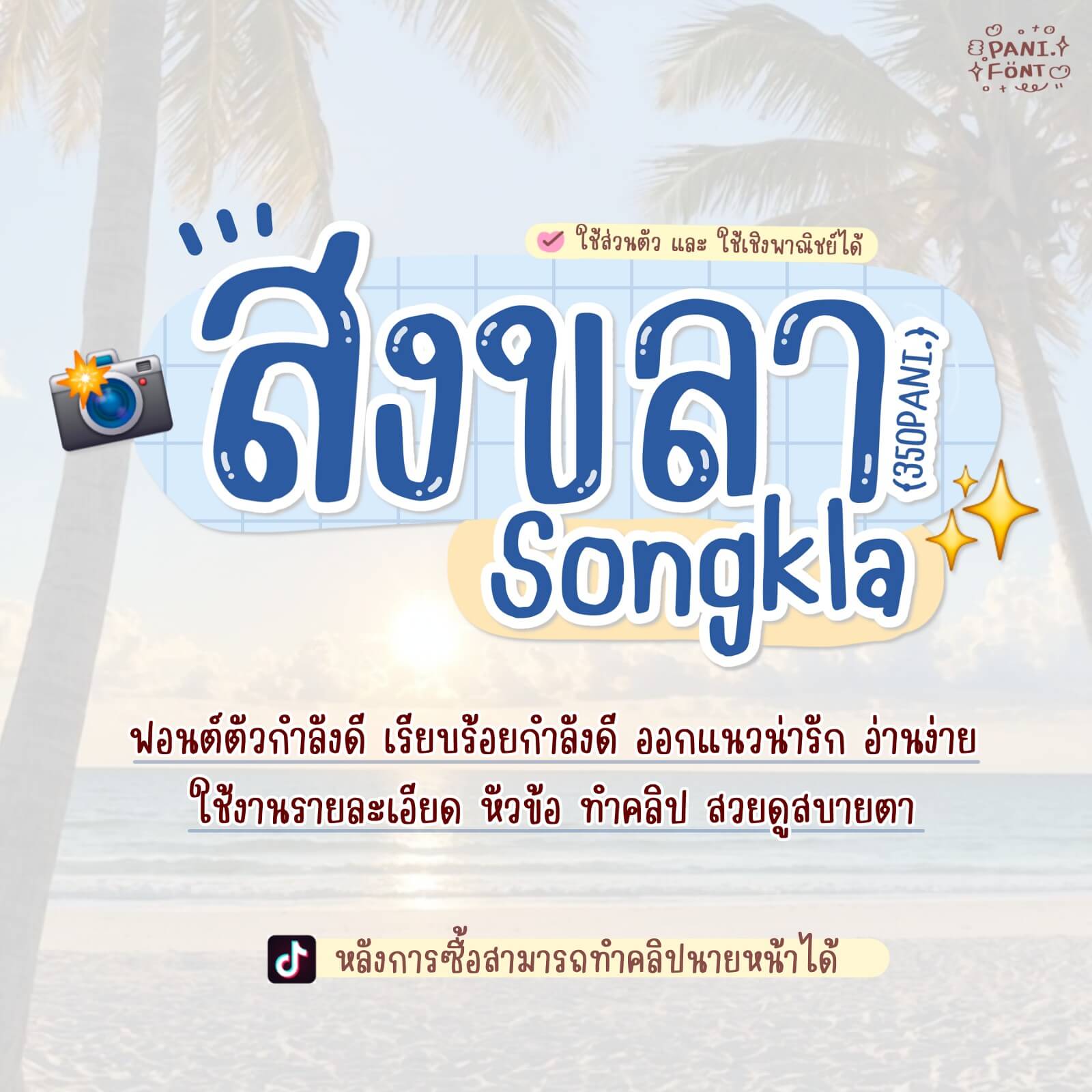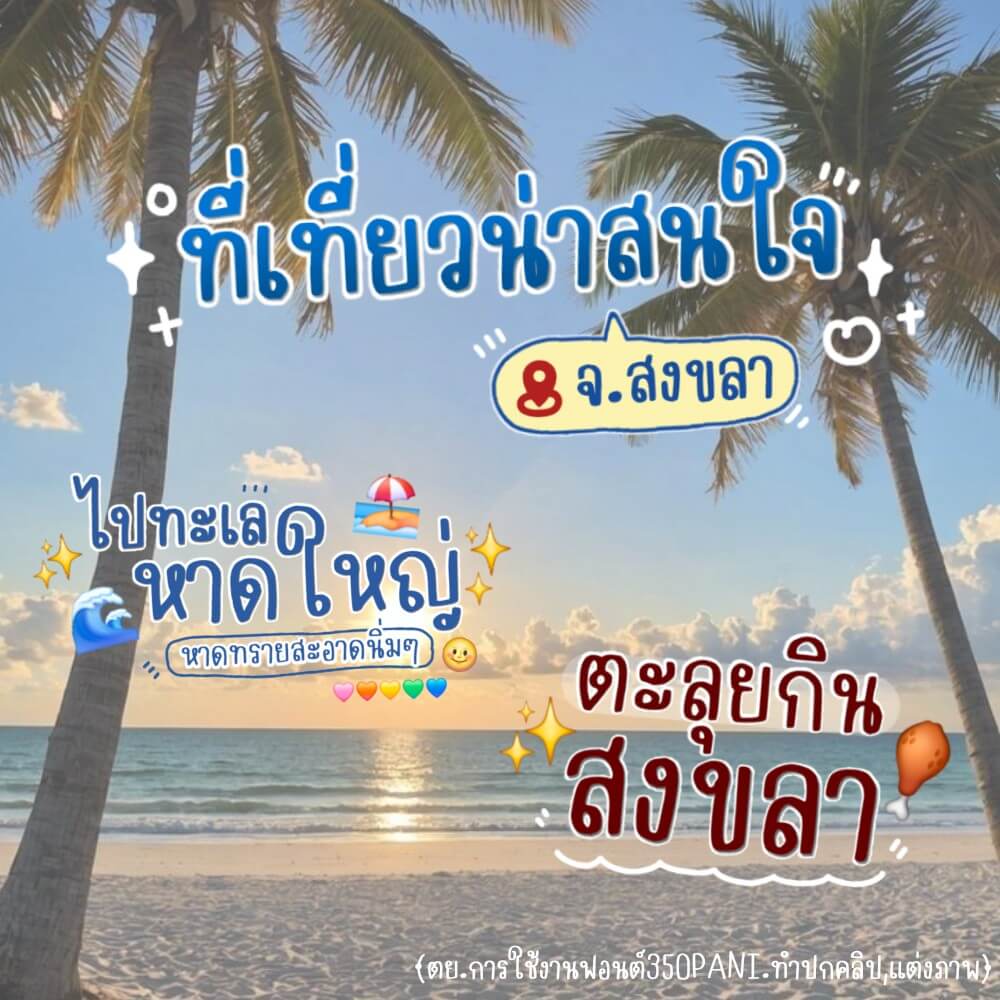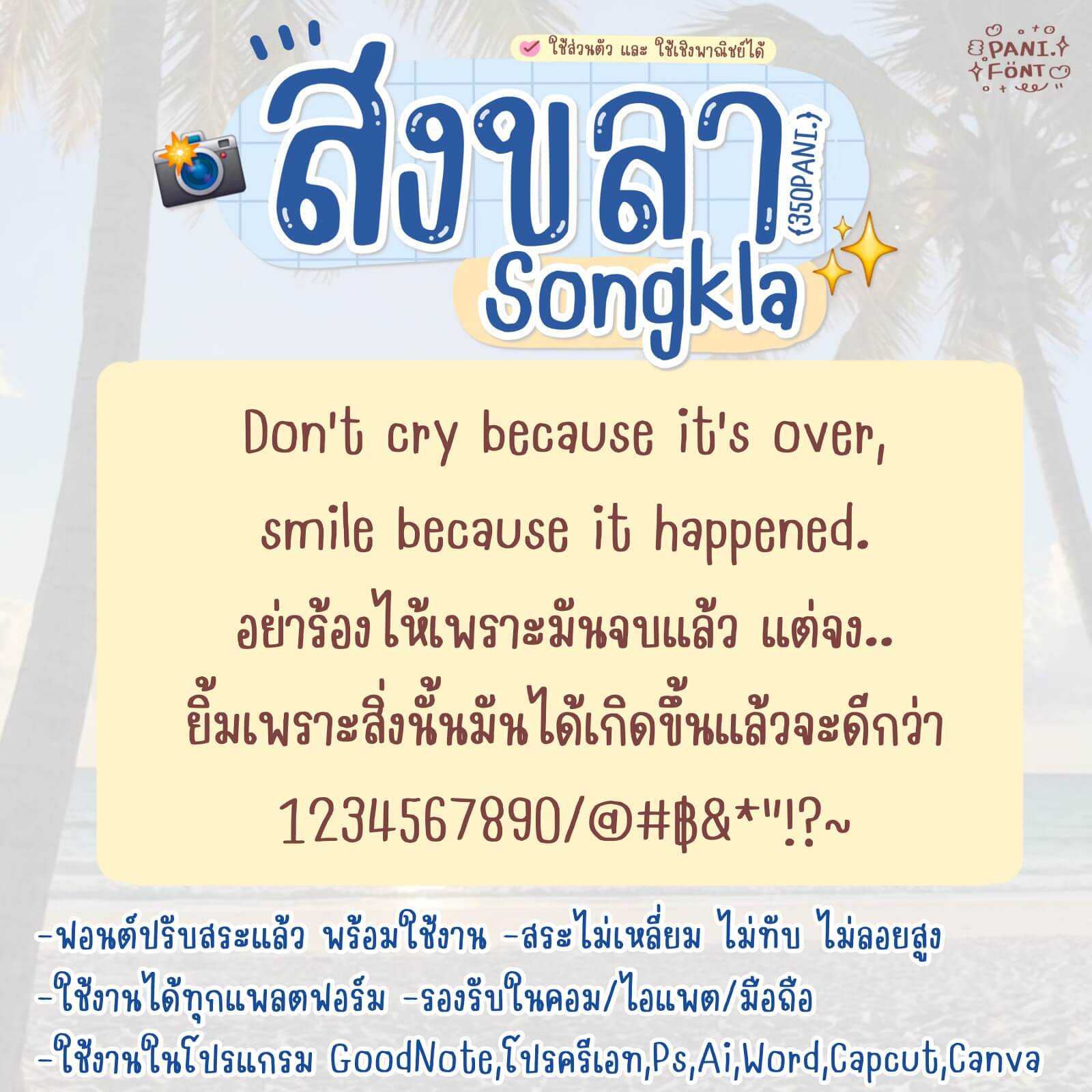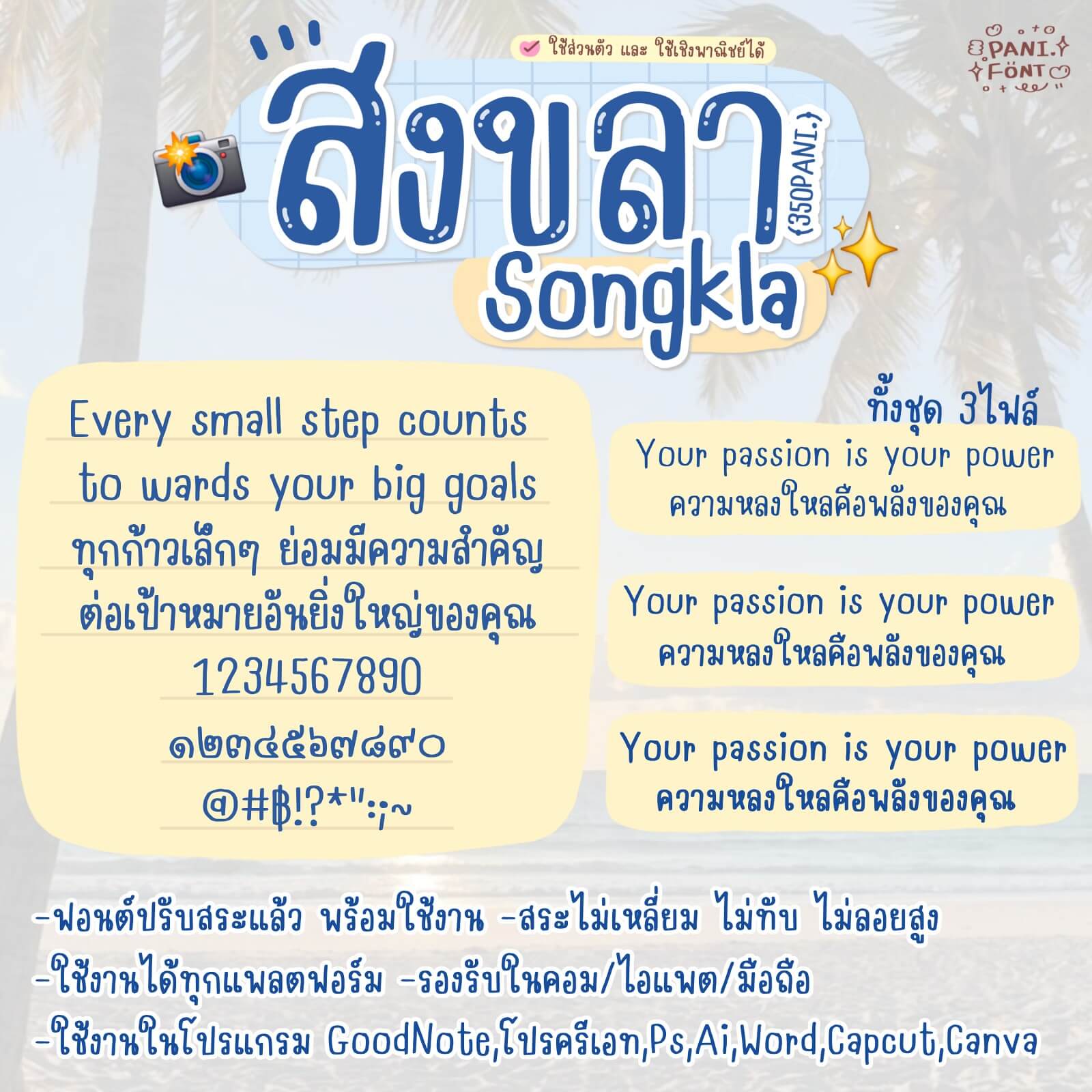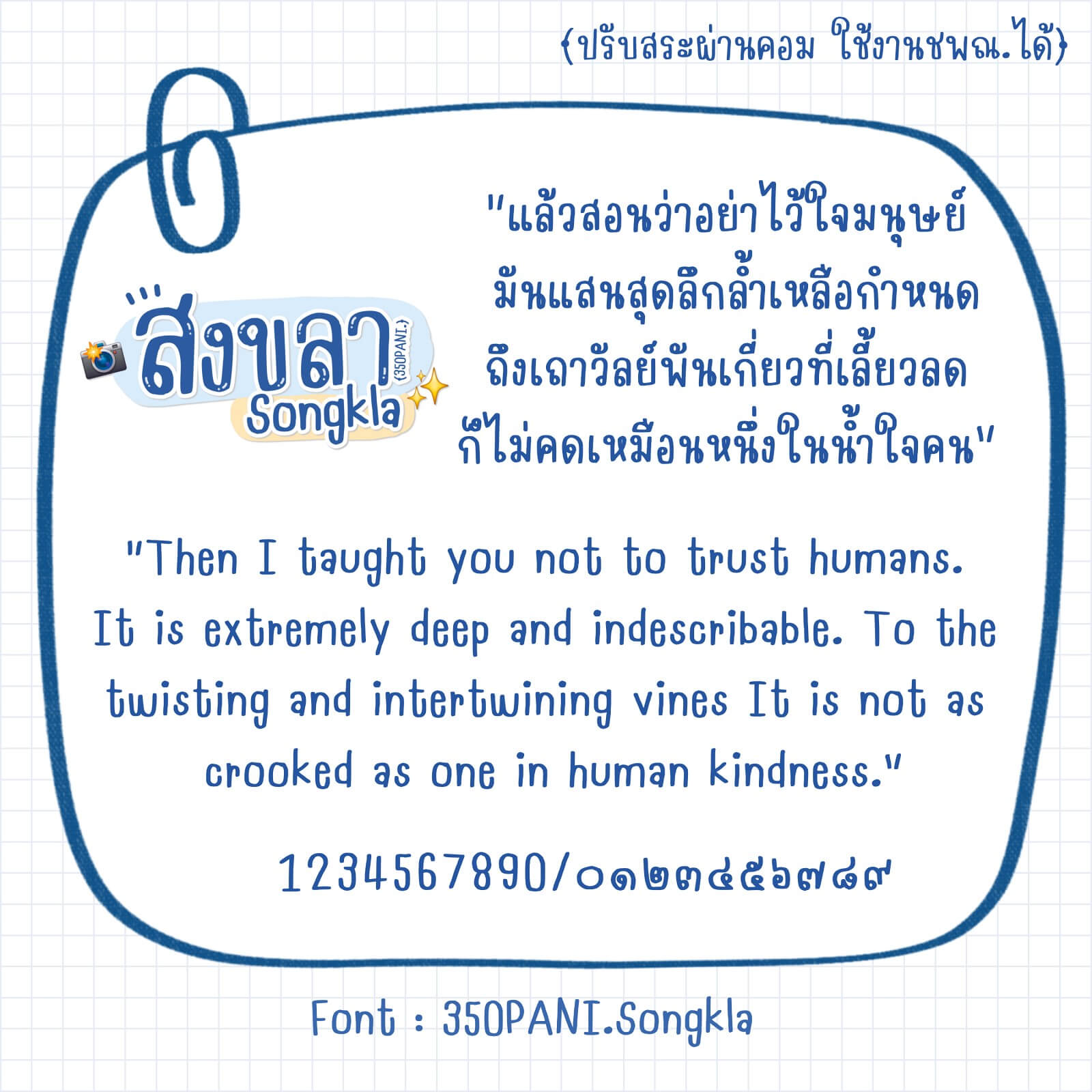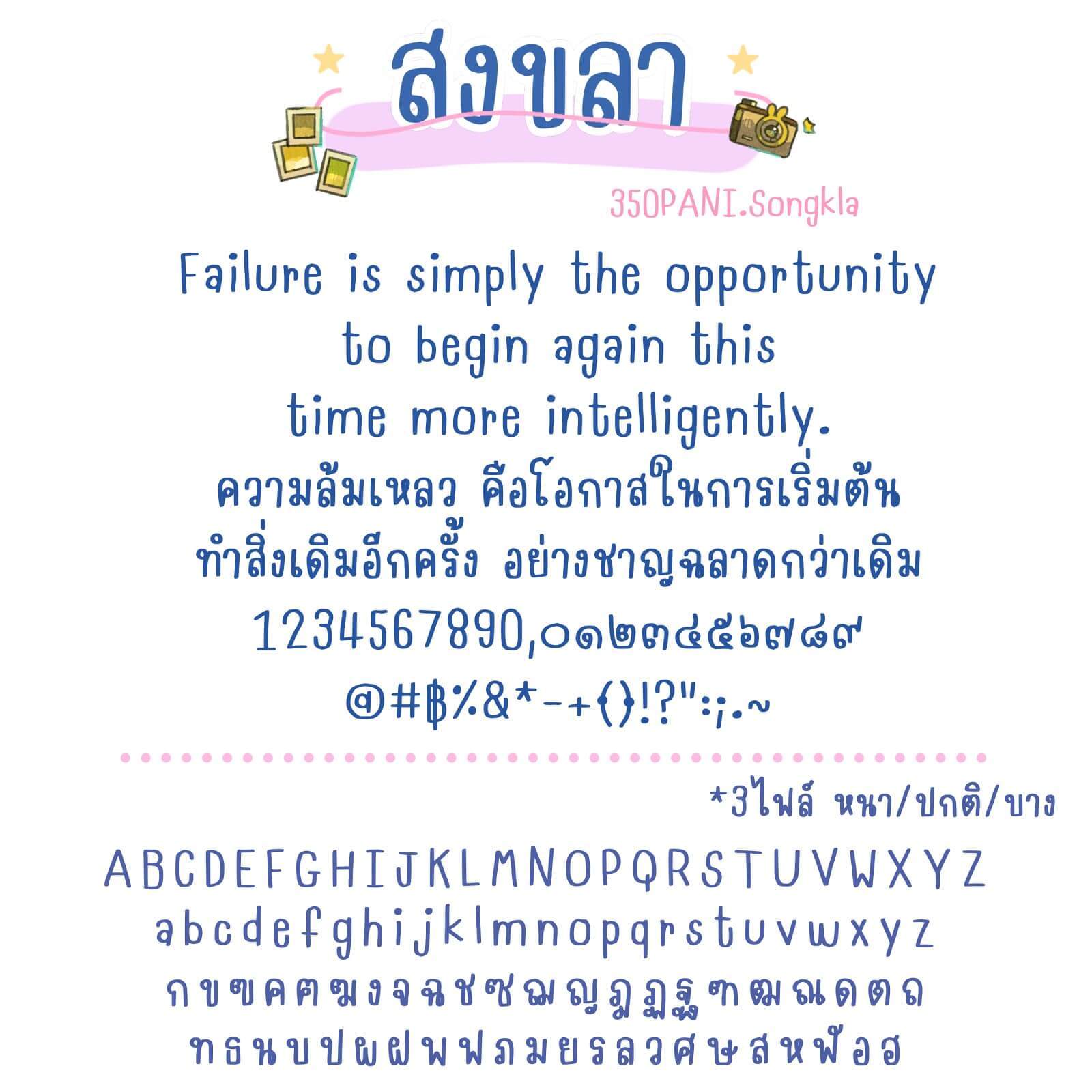
350PANI.สงขลา
ฟอนต์ 350PANI.สงขลา – ฟอนต์ตัวกำลังดี เรียบร้อยกำลังดี ออกแนวน่ารัก อ่านง่าย ใช้งานรายละเอียด หัวข้อ ทำคลิป สวยดูสบายตา แนวนี้น่าจะถูกใจหลายคนเลย เพราะมาทั้งความเรียบร้อย และน่ารักในชุดเดียว ใช้ไม่มีเบื่อแน่นอน
สายทำคลิป ทำป้าย / ตั้งเป็นฟอนต์เครื่อง / จดโน้ต เป็นฟอนต์ที่ควรมีลงคลังไว้เลือกใช้ค่ะ